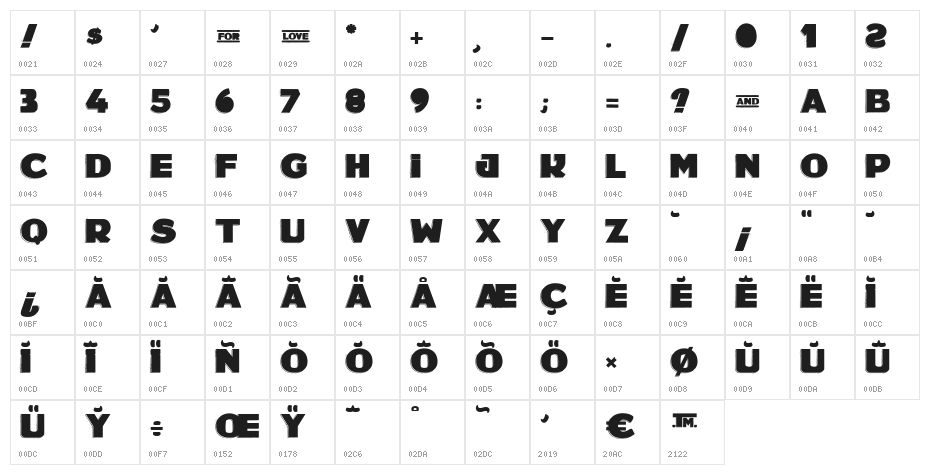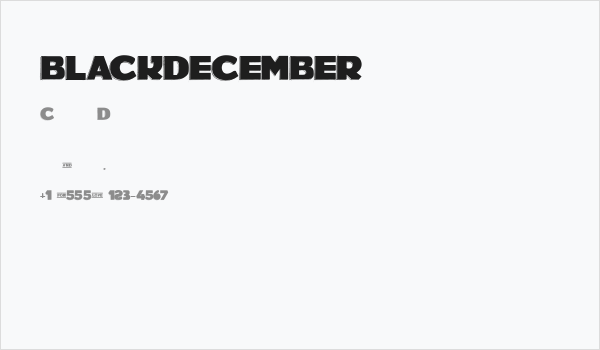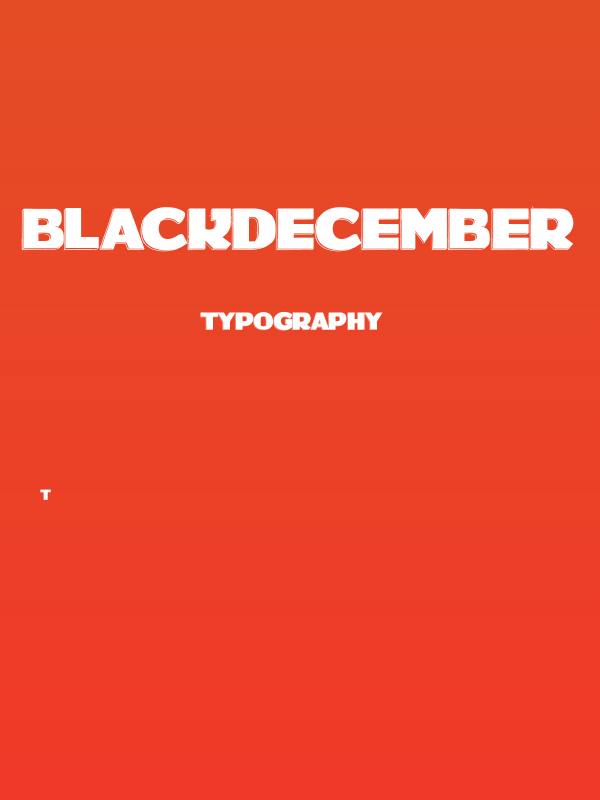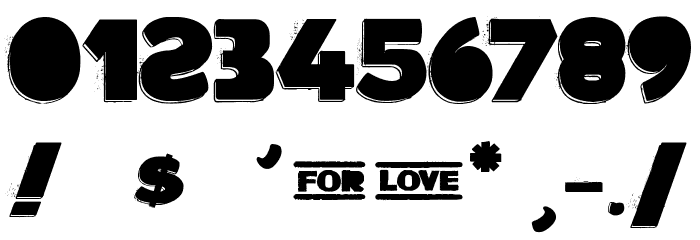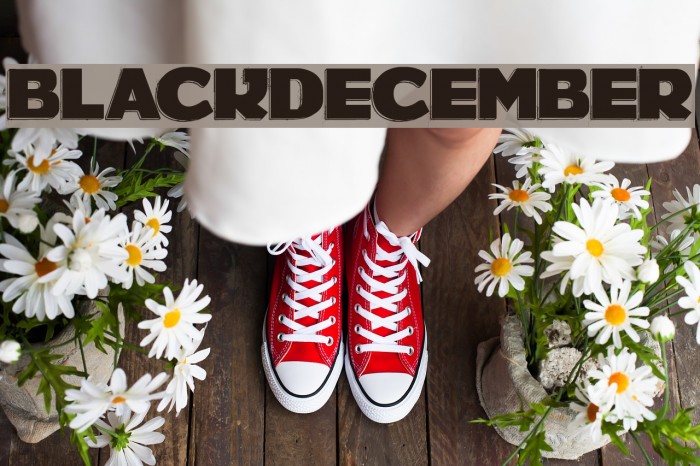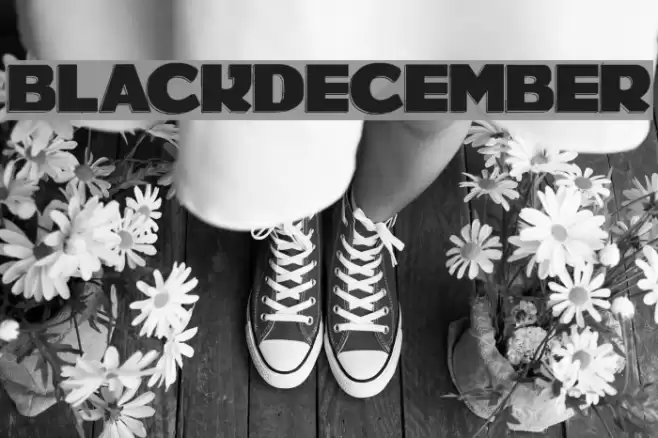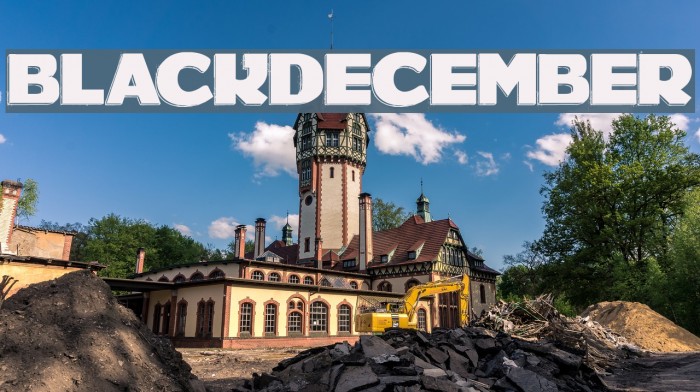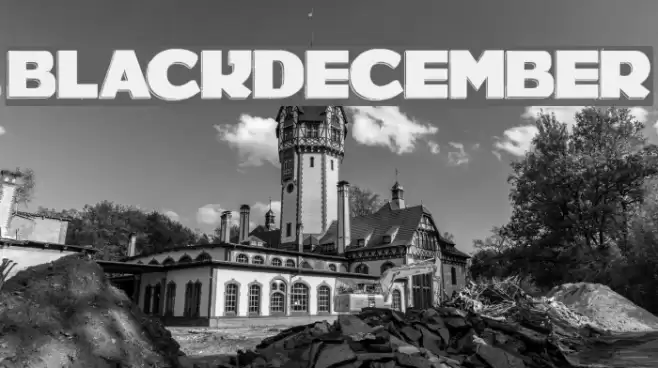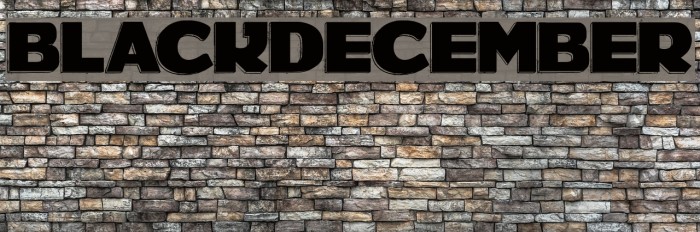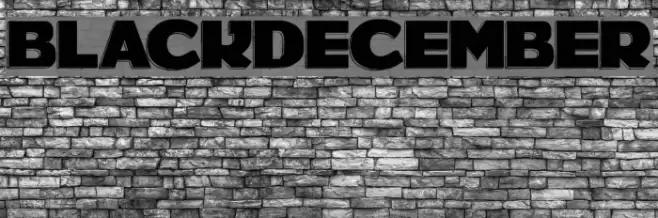
BLACKDECEMBER Font
Fonts by Maelle.K - Thomas Boucherie
| Gesamtstil | Vintage, Modern |
| Vorgeschlagene Projekte | Ideal for posters, headlines, branding, and any project needing a strong visual impact. |